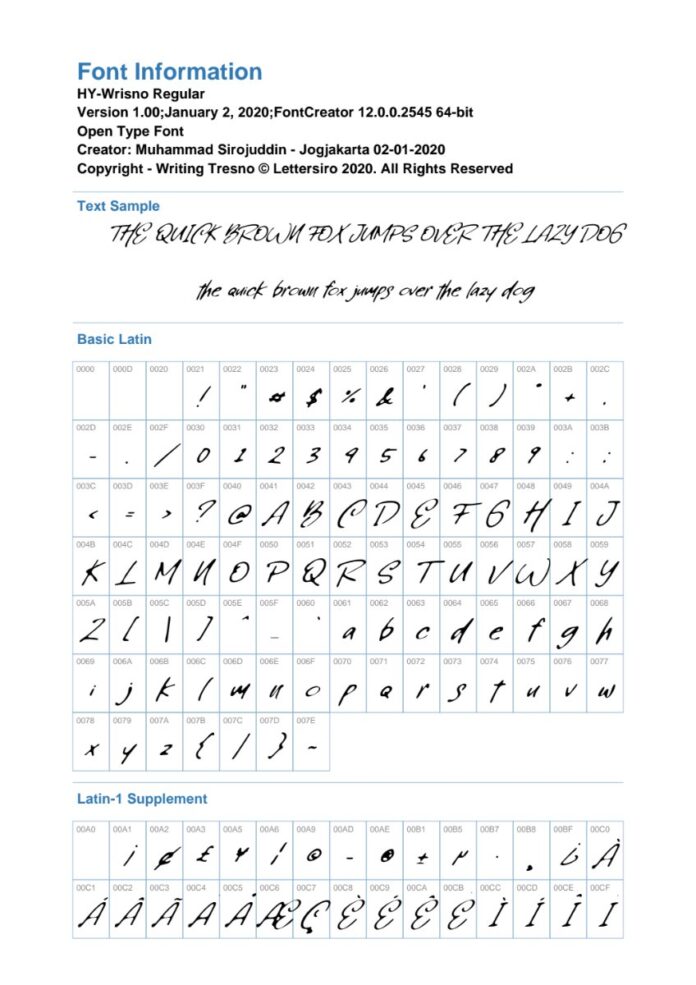
Font HY-Wrisno – Chữ viết tay đẹp
Trong thế giới thiết kế đồ họa, việc lựa chọn font chữ phù hợp có vai trò cực kỳ quan trọng, quyết định đến cảm xúc và thông điệp mà tác phẩm muốn truyền tải. Nếu bạn đang tìm kiếm một phông chữ mang đậm nét cá tính, sự mềm mại và phóng khoáng của chữ viết tay, thì Font HY-Wrisno chính là lựa chọn hoàn hảo. Tại Poster.vn, chúng tôi tự hào mang đến cho bạn tài nguyên font chữ chất lượng cao này, giúp nâng tầm mọi dự án thiết kế của bạn.
Font HY-Wrisno là gì?
Font HY-Wrisno là một phông chữ thuộc thể loại script (viết tay), được thiết kế với những nét chữ mềm mại, uyển chuyển và có phần ngẫu hứng, mô phỏng chân thực nét chữ viết tay tự nhiên. Với phong cách độc đáo này, HY-Wrisno mang đến cảm giác gần gũi, thân thiện nhưng không kém phần nghệ thuật và chuyên nghiệp. Đây là một phông chữ được phát triển bởi Muhammad Sirojuddin và Lettersiro 2020, đảm bảo chất lượng và tính thẩm mỹ cao.
Đặc điểm nổi bật của Font HY-Wrisno
• Phong cách viết tay tự nhiên: Các ký tự của HY-Wrisno được thiết kế tỉ mỉ, mô phỏng hoàn hảo nét chữ viết tay, tạo cảm giác chân thực và cá tính.
• Đa dạng ký tự: Font hỗ trợ đầy đủ các ký tự Latin cơ bản, số và các ký tự đặc biệt, giúp bạn dễ dàng sử dụng trong nhiều ngữ cảnh khác nhau.
• Tính linh hoạt cao: Dù là tiêu đề, logo, thiệp mời hay các ấn phẩm quảng cáo, HY-Wrisno đều có thể thích ứng và tạo điểm nhấn ấn tượng.
• Dễ đọc: Mặc dù là font viết tay, HY-Wrisno vẫn đảm bảo tính dễ đọc, không gây khó khăn cho người xem.
Ứng dụng của Font HY-Wrisno trong thiết kế
Với vẻ đẹp độc đáo và sự linh hoạt của mình, Font HY-Wrisno có thể được ứng dụng rộng rãi trong nhiều lĩnh vực thiết kế khác nhau:
1. Thiết kế Logo và Nhận diện thương hiệu
HY-Wrisno là lựa chọn tuyệt vời cho các thương hiệu muốn thể hiện sự sáng tạo, cá tính và gần gũi. Một logo sử dụng font này sẽ tạo ấn tượng mạnh mẽ, khó quên và mang đậm dấu ấn riêng.
2. Thiệp mời và Thiệp chúc mừng
Với những nét chữ mềm mại, HY-Wrisno rất phù hợp để thiết kế thiệp cưới, thiệp sinh nhật, thiệp chúc mừng các dịp lễ. Nó mang đến cảm giác ấm áp, thân mật và trang trọng.
3. Ấn phẩm quảng cáo và Marketing
Từ banner, poster, flyer cho đến các bài đăng trên mạng xã hội, HY-Wrisno có thể giúp thông điệp của bạn nổi bật hơn, thu hút sự chú ý của khách hàng. Đặc biệt phù hợp với các sản phẩm thủ công, thời trang, mỹ phẩm hoặc dịch vụ mang tính cá nhân hóa.
4. Thiết kế sách, tạp chí và blog
Sử dụng HY-Wrisno cho tiêu đề chương, trích dẫn hoặc các phần đặc biệt trong sách, tạp chí, blog sẽ tạo điểm nhấn nghệ thuật, giúp nội dung trở nên sinh động và hấp dẫn hơn.
5. Thiết kế bao bì sản phẩm
Đối với các sản phẩm thủ công, thực phẩm hữu cơ hoặc các mặt hàng có yếu tố cá nhân hóa, HY-Wrisno sẽ giúp bao bì trở nên độc đáo và thu hút, thể hiện sự tinh tế của thương hiệu.